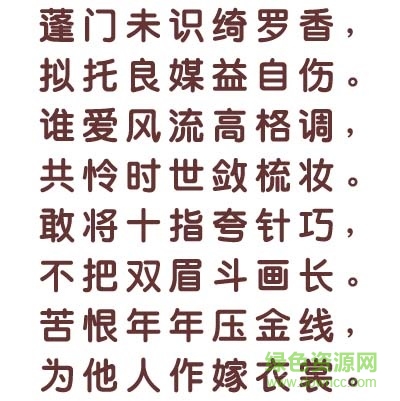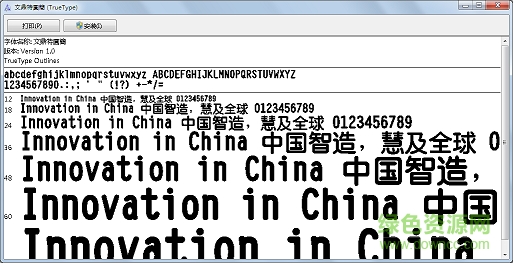
文鼎特圓簡(jiǎn)字體是適合用于多個(gè)不同領(lǐng)域的中文字體,這款字體可以用于出版印刷、廣告設(shè)計(jì)、商業(yè)用字等,現(xiàn)在綠色資源網(wǎng)小編為大家?guī)砻赓M(fèi)下載地址,有需要的用戶趕快來體驗(yàn)吧!
文鼎特圓簡(jiǎn)字體是一款非常圓潤(rùn)的中文簡(jiǎn)體字體,并且筆畫偏錯(cuò),不僅windows系統(tǒng)可以使用,mac系統(tǒng)也可以使用!